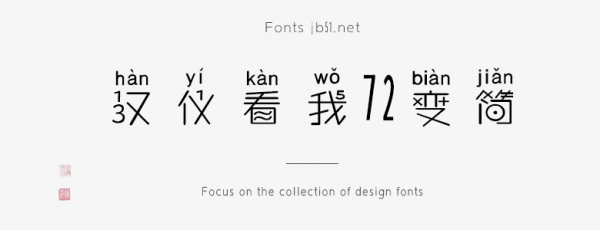
漢儀看我72變簡是由漢儀字庫出品,字體筆觸纖細(xì),字體中點(diǎn)綴了一些數(shù)字,具有很好的視覺感,適合應(yīng)用于藝術(shù)設(shè)計(jì)、平面宣傳設(shè)計(jì)、網(wǎng)頁設(shè)計(jì),書法字帖等領(lǐng)域,需要的朋友可以前來本站下載。